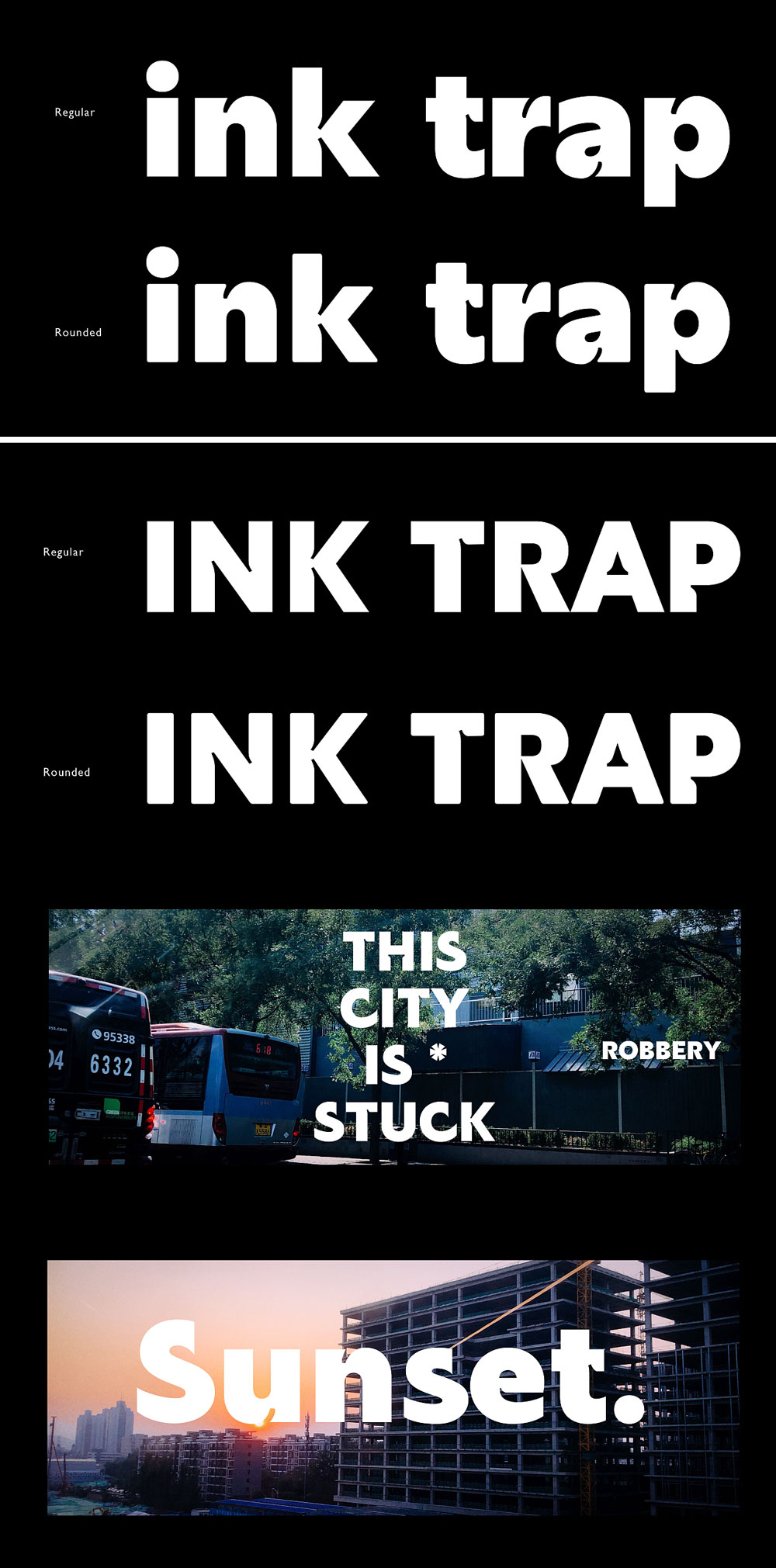
Butter Sans
Butter Sans字体介绍
Butter Sans是北京的设计师李扑通创作的一款英文字体,是时下较为流下的 ink trap 风格,包含 Rounded 款。因字重接近 black 比较粗,适合用在标题类。Butter Sans首发于站酷,作者声明免费商用。
Butter Sans字体应用示例